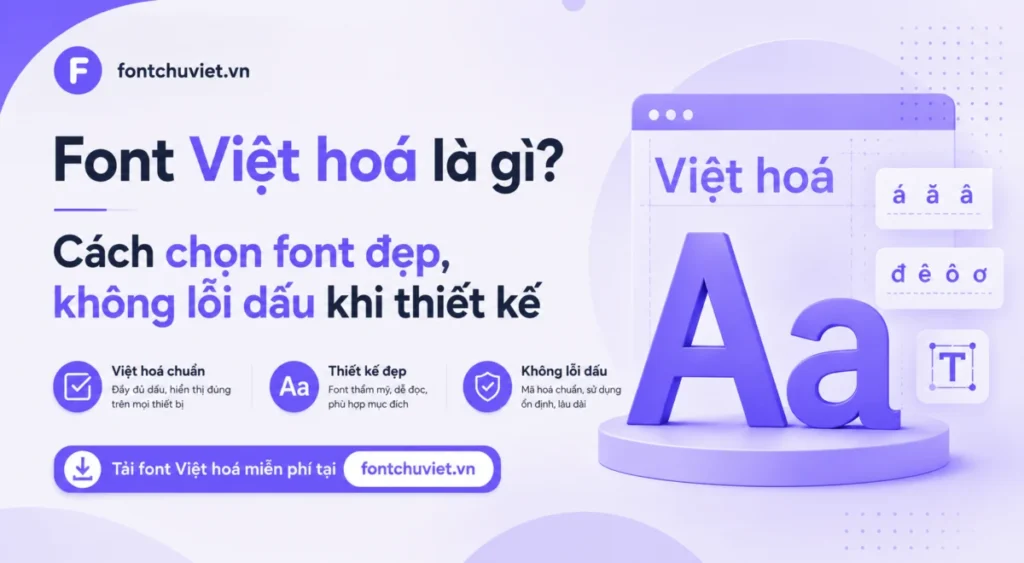
Font Việt hoá là gì? Cách chọn font đẹp, không lỗi dấu khi thiết kế
Nếu bạn từng tải một font chữ rất đẹp về máy nhưng khi gõ tiếng Việt lại bị lỗi dấu, mất chữ hoặc hiển thị kỳ lạ thì rất có thể đó là font chưa hỗ trợ tiếng Việt đầy đủ.
Đây cũng là lý do ngày càng nhiều người tìm kiếm font Việt hóa khi làm thiết kế, chỉnh sửa ảnh hoặc sáng tạo nội dung.
Vậy font Việt hóa là gì, vì sao cần dùng và làm sao chọn được font đẹp mà không lỗi dấu khi thiết kế? Hãy cùng tìm hiểu trong bài viết này.
Font Việt hóa là gì?
Font Việt hóa là font chữ đã được bổ sung hoặc tối ưu bộ ký tự tiếng Việt để có thể hiển thị đầy đủ dấu khi gõ.
Điều này bao gồm:
- Ký tự tiếng Việt như ă, â, ê, ô, ơ, ư, đ
- Dấu sắc, huyền, hỏi, ngã, nặng
- Khoảng cách dấu cân đối hơn
- Hiển thị ổn định trong phần mềm thiết kế
Nói đơn giản, font Việt hóa giúp bạn gõ tiếng Việt đúng, đẹp và không bị lỗi khi thiết kế.
Ví dụ:
Một font quốc tế có thể rất đẹp khi viết tiếng Anh nhưng khi gõ:
“Thiết kế banner đẹp cho quán cafe”
thì dấu tiếng Việt có thể bị lệch, mất chữ hoặc hiển thị không cân đối.
Khi đã được Việt hóa, các lỗi này sẽ được xử lý để font hoạt động tốt hơn với tiếng Việt.
Vì sao thiết kế nên dùng font Việt hóa?
Nhiều người mới học thiết kế thường chọn font theo cảm tính, thấy đẹp là tải về.
Tuy nhiên, nếu font không hỗ trợ tiếng Việt tốt thì khi làm banner, poster hoặc logo sẽ gặp rất nhiều vấn đề.
Một font không lỗi dấu sẽ giúp:
- Thiết kế chuyên nghiệp hơn
- Nội dung dễ đọc hơn
- Không mất thời gian sửa lỗi chữ
- Typography đẹp và cân đối hơn
- Làm việc nhanh hơn trong Photoshop hoặc Illustrator
Đặc biệt nếu làm thiết kế cho khách hàng, lỗi dấu tiếng Việt là điều rất dễ làm giảm chất lượng sản phẩm.
Những lỗi thường gặp khi dùng font chưa Việt hóa
Nếu bạn từng thấy chữ hiển thị kỳ lạ khi gõ tiếng Việt thì có thể đang gặp một trong những lỗi sau:
Mất dấu tiếng Việt
Ví dụ:
“Thiết kế” thành “Thiet ke”
Điều này thường xảy ra khi font không có bộ ký tự Unicode tiếng Việt.
Dấu bị lệch hoặc chồng lên chữ
Một số font có hỗ trợ tiếng Việt nhưng căn chỉnh chưa tốt khiến dấu nhìn rất khó chịu.
Ví dụ:
- Dấu quá cao
- Dấu đè lên chữ
- Khoảng cách mất cân đối
Điều này ảnh hưởng khá nhiều tới typography hoặc thiết kế banner lớn.
Thiếu ký tự tiếng Việt
Một số font thiếu:
- Đ
- Ơ
- Ư
- Ă
- Â
Hoặc chữ in hoa tiếng Việt hiển thị lỗi.
Cách chọn font đẹp mà không lỗi dấu khi thiết kế
Không phải font đẹp nào cũng phù hợp để dùng.
Dưới đây là một vài cách chọn font giúp thiết kế đẹp hơn và hạn chế lỗi.
Ưu tiên font đã Việt hóa đầy đủ
Đây là tiêu chí quan trọng nhất.
Khi tải font, hãy kiểm tra:
- Có hỗ trợ tiếng Việt không
- Có đầy đủ dấu không
- Hiển thị ổn định khi viết hoa, viết thường không
Một mẹo đơn giản là thử gõ:
ÁÀẢÃẠ ĂẮẰẲẴẶ ÂẤẦẨẪẬ Đ ÊẾỀỂỄỆ ÔỐỒỔỖỘ ƠỚỜỞỠỢ ƯỨỪỬỮỰ
Nếu hiển thị đẹp, khoảng cách ổn thì font thường dùng ổn.
Chọn font theo mục đích thiết kế
Mỗi kiểu thiết kế nên dùng nhóm font khác nhau.
Banner quảng cáo → font đậm, rõ ràng.
Typography quote → handwritten hoặc display.
Logo thương hiệu → serif hoặc sans serif hiện đại.
Nội dung nhiều chữ → ưu tiên dễ đọc.
Một lỗi phổ biến của người mới là dùng font quá nghệ thuật cho nội dung dài khiến người xem rất khó đọc.
Không dùng quá nhiều font trong cùng thiết kế
Một layout dùng quá nhiều font sẽ dễ rối mắt.
Thông thường:
- 1 font tiêu đề
- 1 font nội dung
- 1 font nhấn mạnh
là đủ cho đa số thiết kế.
Font Việt hóa dùng tốt trong phần mềm nào?
Các font Việt hóa hiện nay thường hoạt động tốt trên:
Kết luận
Hiểu đúng font Việt hóa là gì sẽ giúp bạn tránh được rất nhiều lỗi khó chịu khi thiết kế bằng tiếng Việt.
Một font đẹp không chỉ cần bắt mắt mà còn phải hiển thị tiếng Việt đầy đủ, cân đối và dễ đọc. Khi chọn đúng font, thiết kế sẽ chuyên nghiệp hơn, sạch hơn và giúp bạn tiết kiệm rất nhiều thời gian xử lý lỗi dấu.